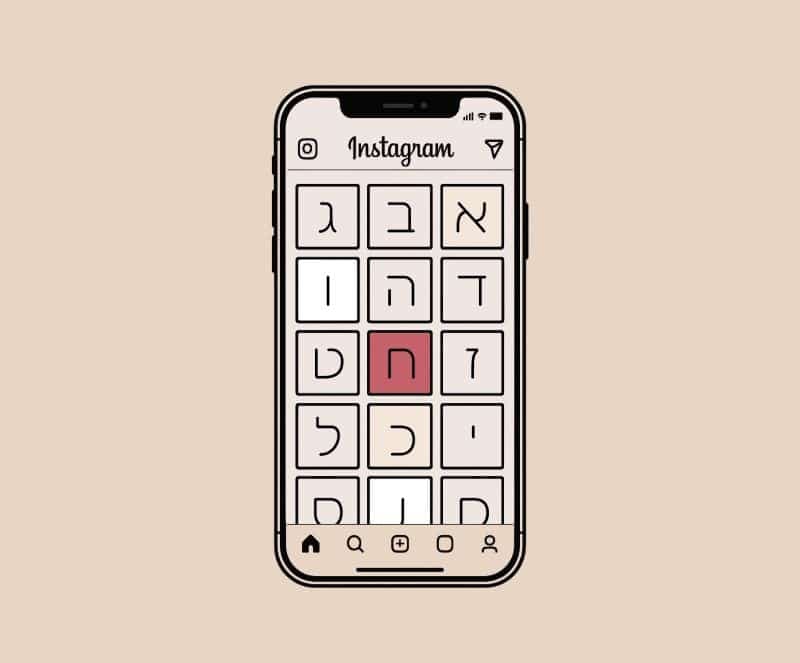
כשרוצים למשוך תשומת לב באינסטגרם, אין דבר חשוב יותר מהמראה. נכון, התוכן הוא המלך – אבל הכתר הוא העיצוב. ובמרכז העיצוב, יש אלמנט אחד שמקבל פחות קרדיט ממה שמגיע לו: הפונט.
הוא זה שמייצר אווירה, יוצר בידול, ומבדיל בין תוכן שנראה כמו שבלונה לבין תוכן עם נוכחות. העולם של פונטים לאינסטגרם הולך ומתפתח, ויחד איתו גם רמת הדרישות של הקהל.
פוסט שכתוב יפה לא מספיק – הוא חייב גם להיראות טוב, להיות נעים לעין, ולהתחבר לזהות המותג. בחירה בפונט המתאים היא לא רק עניין אסתטי, אלא כלי תקשורת של ממש.
במאמר הזה נציג חמישה טיפים שיעזרו לכם להשתמש בצורה חכמה ונכונה בפונטים ברשת האינסטגרם.
לפני שאתם מתלהבים מפונט טרנדי שראיתם אצל מישהו אחר, עצרו רגע. תשאלו את עצמכם: האם הוא מייצג אותי? הפונטים צריכים לשדר את האישיות של המותג – בין אם מדובר בעסק קופצני, בעמותה רצינית או בבלוגרית לייף־סטייל.
פונט עגול ורך יכול לשדר רוך ונגישות, בעוד שפונט דק ואלגנטי יעביר יוקרה ואסתטיקה. ההמלצה: צרו לעצמכם רשימת ערכים שמייצגים אתכם – ובחרו פונט שתואם להם ויזואלית.
כשעובדים עם פונטים בעברית שמתכתבים עם האישיות של המותג, החיבור הזה בין ערכים לעיצוב עושה לעיתים קרובות את ההבדל בין תוכן שגולל הלאה – לבין תוכן שעוצר נשימה.
אינסטגרם הוא קודם כול פלטפורמה לנייד, ולכן פונטים לאינסטגרם בעברית צריכים להיות ברורים גם בגודל קטן. טקסט שנראה נהדר במחשב עלול להפוך ללא־קריא בסטורי.
הטריק הוא לבחור פונט שיש לו ריווח טוב בין האותיות, קונטרסט ברור, ומבנה שלא "נמרח" כשהוא מוקטן. נסו לבדוק את הפונט על תמונה אמיתית מהפיד שלכם – ותראו אם הוא עדיין עושה את העבודה.
אל תסתפקו בצפייה בעיצוב על מסך גדול – עברו לטלפון, צלמו מסך, בדקו צבעים, ובדקו ניגודיות. לפעמים שינוי קטן בגודל או בעובי הפונט משנה הכול.
פיתוי נפוץ הוא לשלב כמה פונטים יחד, כדי לגוון את העיצוב. אבל באינסטגרם, פחות זה יותר. בחירה בפונט אחד טוב (או מקסימום שניים) יוצרת מראה נקי, אסתטי ומקצועי – במיוחד כשמחפשים פונטים לאינסטגרם שמצטלמים טוב ויוצרים זהות גרפית עקבית.
כדי לשבור את המונוטוניות, אפשר לשחק עם משקל (bold/light), צבע או גודל – מבלי לוותר על האחידות הגרפית. אם אתם עובדים עם פונטים בעברית עם ניקוד, הקפידו במיוחד על קריאות ברורה ושילוב שמכבד את הסגנון של הטקסט. כך הפונט יבלוט – ולא יתחרה על תשומת הלב מול עצמו.
שימוש חכם במרחב הלבן שסביב הטקסט, מרווחי שורות מאוזנים והימנעות מעומס מיותר – אלה האלמנטים שמייחדים עיצוב טוב. תנו לאותיות שלכם לנשום, והן יגמלו לכם בחזות מזמינה.
אם התוכן שלכם כולל ציטוטים, פסוקים או מילים שדורשות ניקוד – השקיעו בבחירה של פונטים, ובעדיפות: חפשו כאלה עם ניקוד. זה קריטי במיוחד כשמדובר בפוסטים חינוכיים, תורניים או כאלה שפונים לילדים, ובמיוחד אם אתם מחפשים פונטים לאינסטגרם שיראו טוב גם במובייל.
פונטים כאלה לא רק נראים טוב יותר – אלא גם משדרים רצינות והשקעה. פונט תנכי עם ניקוד, למשל, יכול להפוך פוסט פשוט לחגיגה גרפית של ממש.
וטיפ נוסף: אם אתם משתמשים בפונט כתב בלון – ודאו שהוא לא מתנגש עם הטקסט המנוקד, כדי לשמור על קריאות מקסימלית.
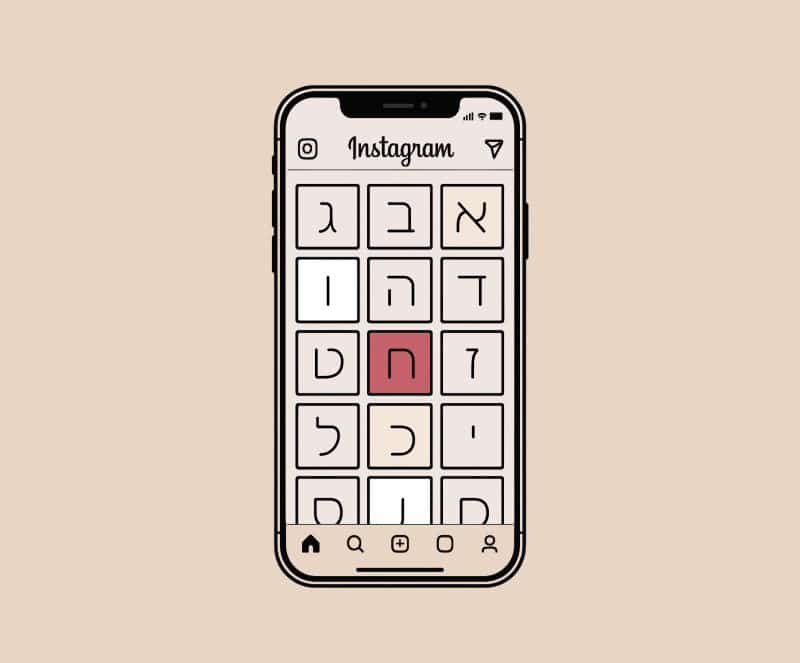
לסיכום, בחירה נכונה של פונטים לאינסטגרם בעברית היא לא רק שאלה של טעם – אלא החלטה עיצובית שמגדירה את הזהות של התוכן. השקעה בבחירת הפונט הנכון, רישוי חוקי וניקוד כשצריך – תעזור לכם לבלוט, להעביר מסר ברור, ולגרום לאנשים לעצור לגלול.
פונט מעוצב יוצר חוויה ויזואלית – הוא מדגיש את המסר, מוסיף אופי, ומחזק את המותג.
אם הטקסט דורש הבהרה או מדובר בציטוט תורני – בהחלט.
מומלץ לא יותר משניים – כדי לשמור על קו אחיד ונעים לעין.